Projekt Manual — časť 1
Úvod 5-dielneho výskumu k projektu Manual, ktorého cieľom je digitalizácia tradičných typov písma používaných v pred-digitálnej ére vo verejnom priestore na Slovensku, ich modernizácia a opätovné uvedenie do používania.
Keď som pred viac ako štyrmi rokmi začal s projektom Type Atlas – online archívom starých nápisov prevažne z obdobia od začiatku 20. storočia po 90. roky (keď sa nápisy začali robiť digitálne) – hľadal som čo najzaujímavejšie, na mieru vytvorené nápisy na starých obchodných domoch, pokazené neóny, socialistické skriptové logá a podobné kuriozity. Vďaka Type Atlasu som si však začal viac všímať nielen takéto nápisy, ale úplne všetku, aj tú najnenápadnejšiu typografiu na ulici – od označení hydrantov, nivelačných bodov, upozornení na elektrických skrinkách, zákazov vstupu, cez čísla domov až po označenie ulíc.
To, čo som zo začiatku nepovažoval za zaujímavé, postupne začalo v mojej hlave vytvárať akýsi systém, písma z týchto technickejších nápisov totiž napriek relatívne veľkej variabilite jednoznačne vykazovali spoločné znaky širšej písmovej rodiny. Túto rodinu som si pre potreby tohto projektu nazval Manual Grotesk.
Hoci sa toto písmo môže javiť ako neutrálne, prípadne pôsobiť technicky až mechanicky, v uličnej typografii sa nestráca – naviguje, upozorňuje alebo informuje nás, môžeme sa naň vždy spoľahnúť. A to kdekoľvek na Slovensku. Táto istota a familiárnosť mu dáva nekomplikovaný, ba až priateľský charakter.
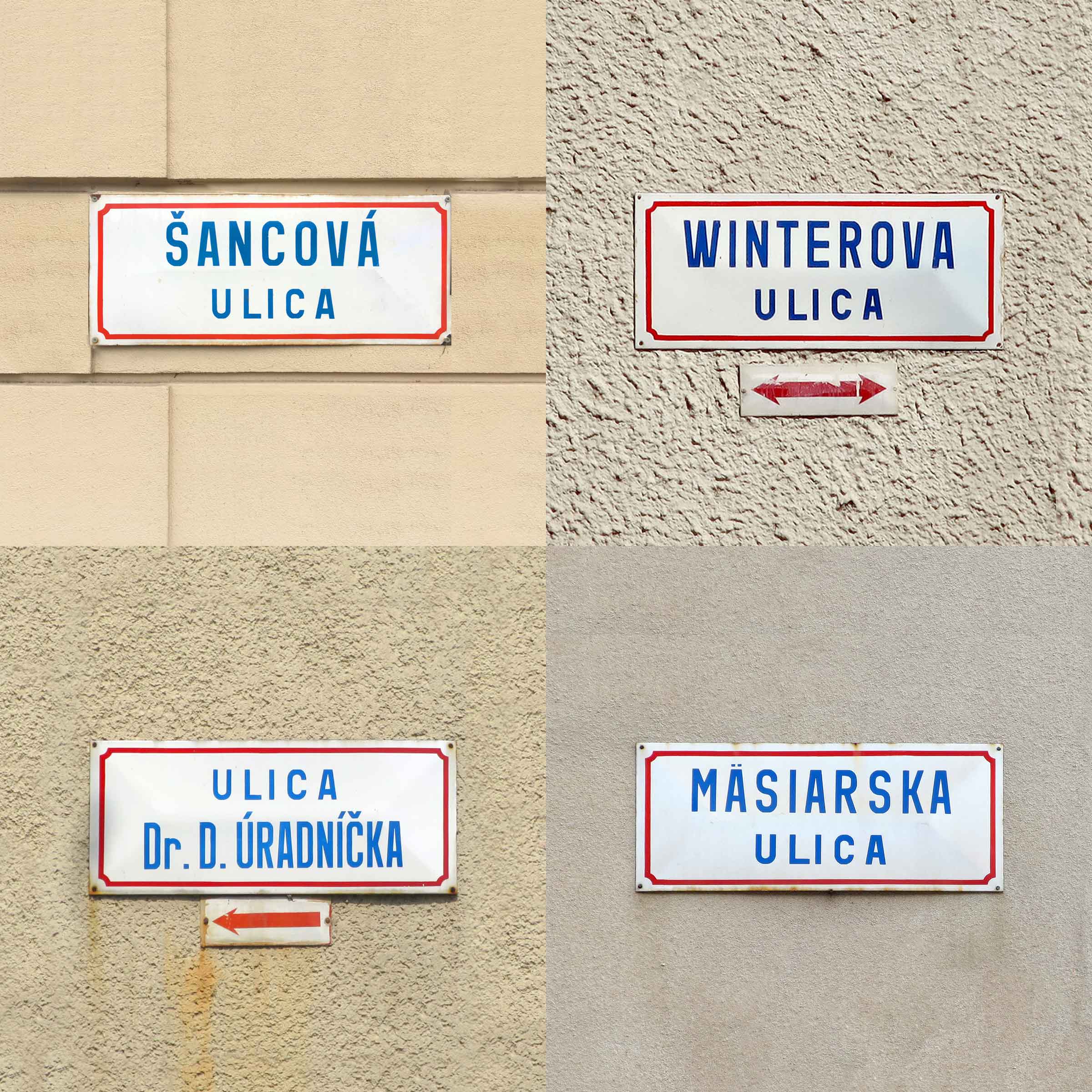
V rámci projektu Type Atlas sa mi podarilo nájsť veľké množstvo variácií tohto písma – ťahy niektorých sú uniformné, iné majú kontrast (tzn. striedanie tučných a tenkých ťahov), niektoré majú oblé zakončenia, iné štvrťkruhové, prípadne ostro zrezané. Existujú v množstve šírok, tučností, kolmé aj naklonené, štandardné aj šablónové. Výskyt niektorých je obmedzený geograficky iba na konkrétne miesto (napr. uličné tabuľky v Banskej Štiavnici, ručne maľovaná navigácia v opustených kúpeľoch Korytnica), iné sú charakteristické pre určitú organizáciu (napr. písmo z rázcestníkov v Tatranskom národnom parku). Všetky však zdieľajú spoločnú konštrukciu a vnútornú logiku.
Môj záujem o tieto na prvý pohľad banálne písma ešte viac narástol, keď som začal čoraz častejšie nachádzať pôvodné uličné smaltové tabuľky nahradené za plastové – verejné priestranstvá alebo domy po zateplení fasády sú označované novými plastovými tabuľkami, ktoré sa v tom lepšom prípade snažia aspoň napodobniť pôvodný dizajn, v tom horšom ho však úplne ignorujú. Plast sa samozrejme používa preto, lebo je lacnejší, pôvodné písmo sa ale nahrádza za zdeformovaný Arial alebo podobné písma preto, lebo jeho digitálna podoba neexistuje.
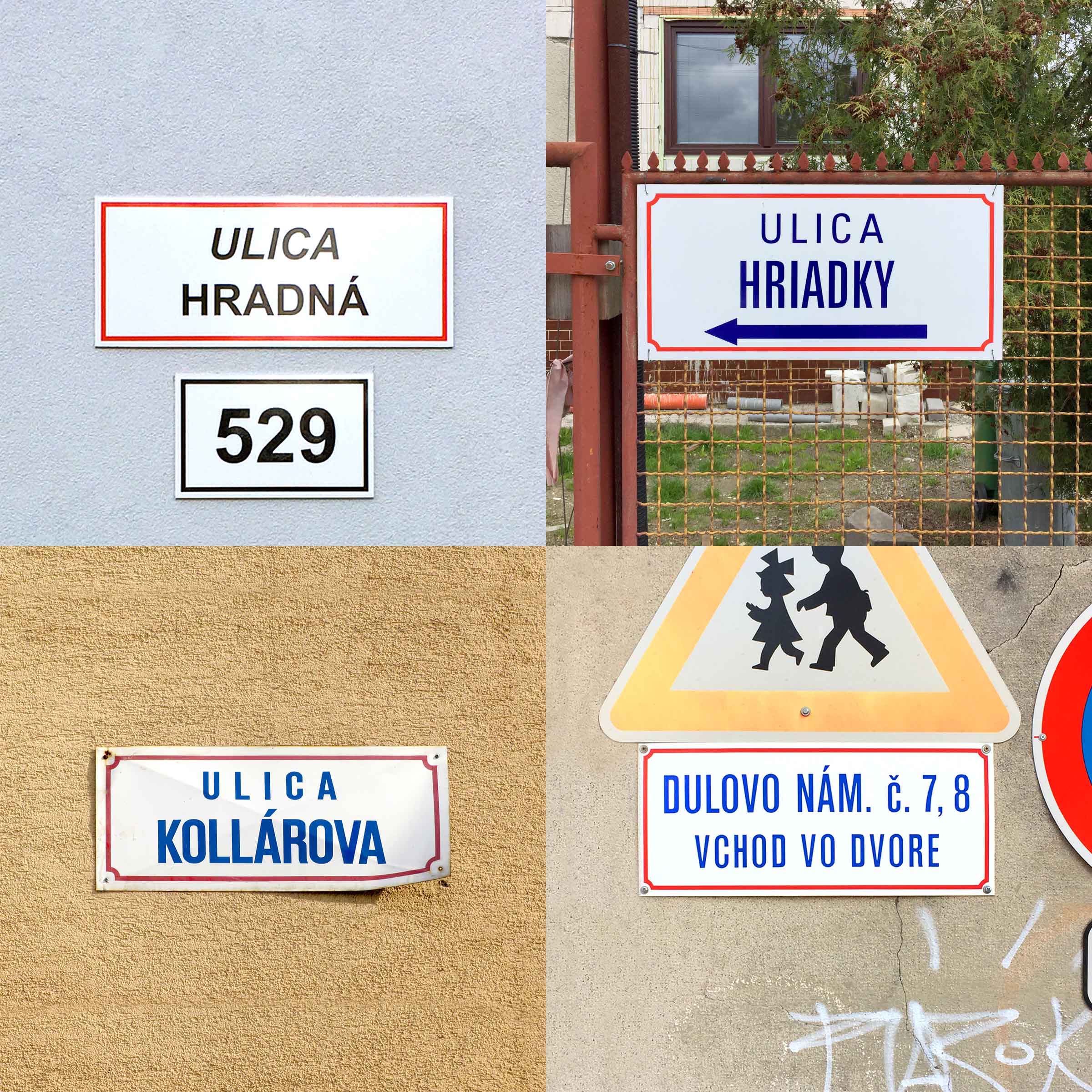
Ako dizajnér písma som sa preto rozhodol skúsiť tento trend zastaviť, digitalizovať tieto písma, distribuovať ich a v rámci možností nájsť ich uplatnenie aj v súčasnom digitálnom grafickom dizajne a typografii.
Niektoré pôvodné písma nie sú z hľadiska modernej typografie úplne dokonalé. Dnešné technológie však umožňujú písmo lepšie konštruovať a použiť širšiu tvarovú variabilitu a dynamické prvky v sadzbe textu. Pri digitalizácii sa tak vďaka tomu pôvodné písma posunú na úroveň súčasných typografických a technologických štandardov. Výsledkom budú digitalizované písma, distribuované v modernom formáte OpenType Font, vhodné pre použitie vo všetkých grafických aplikáciách i na webe.